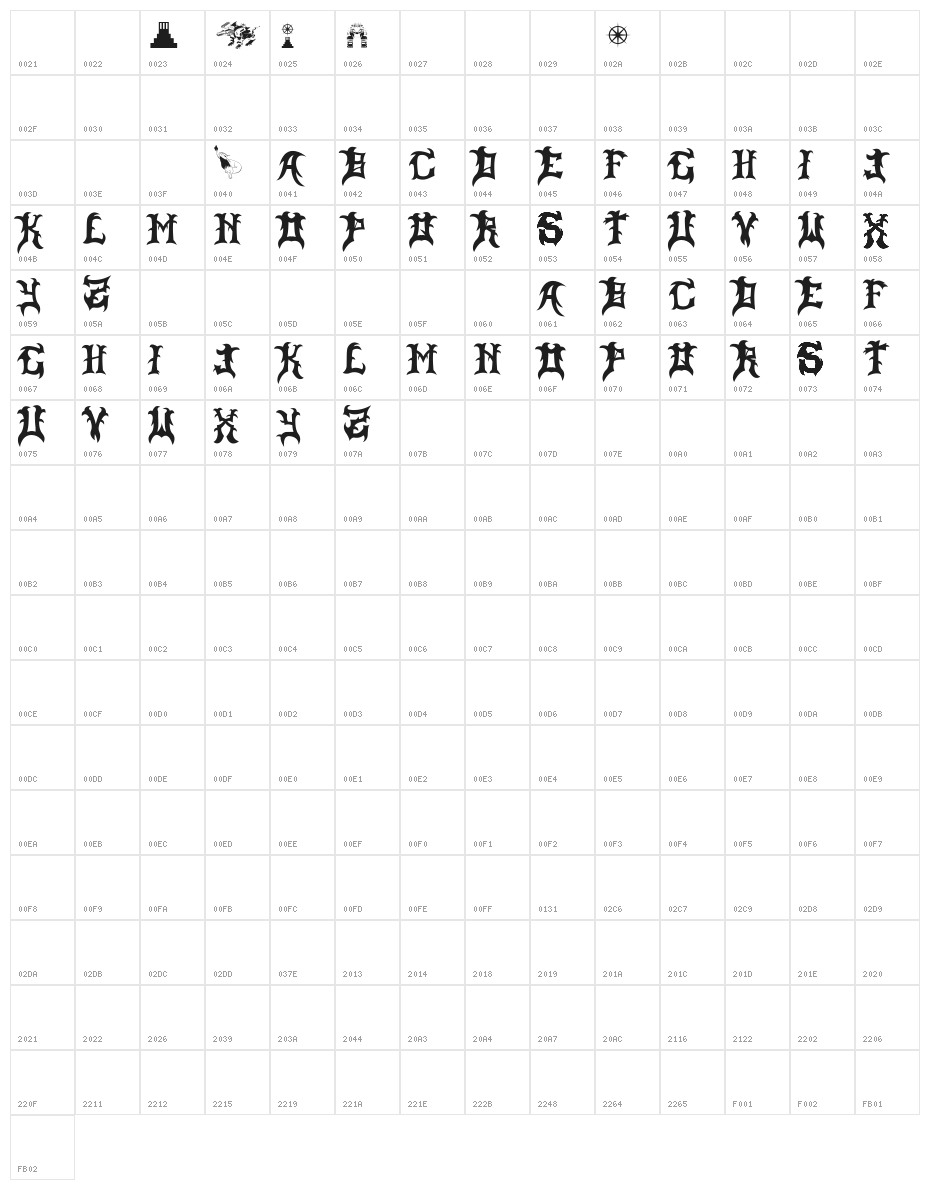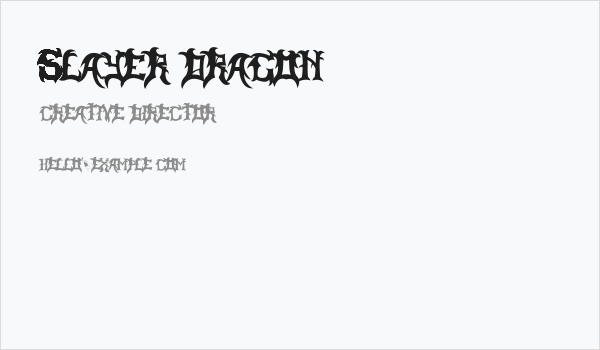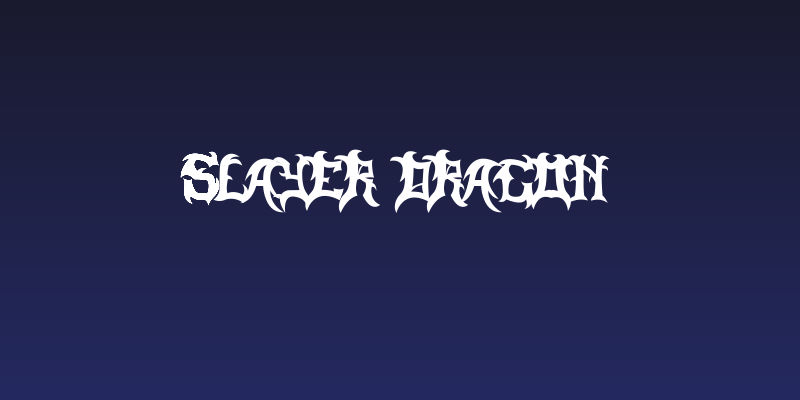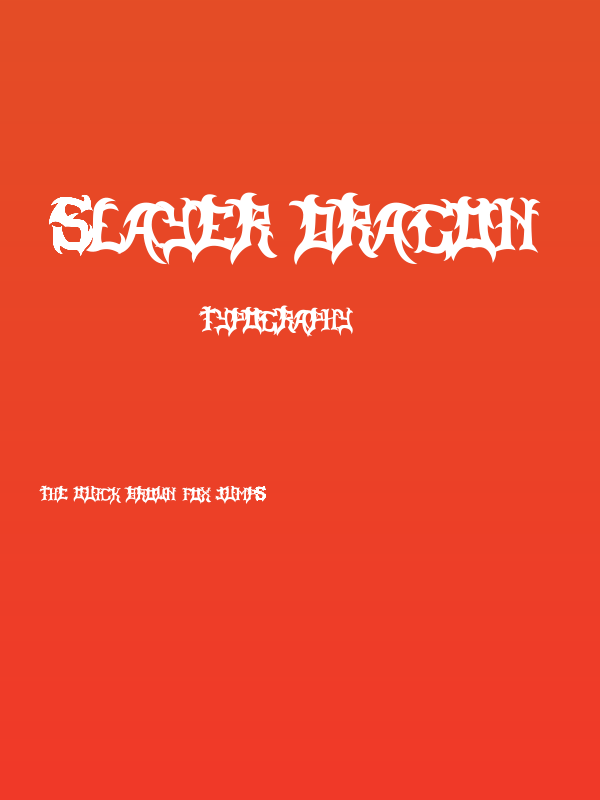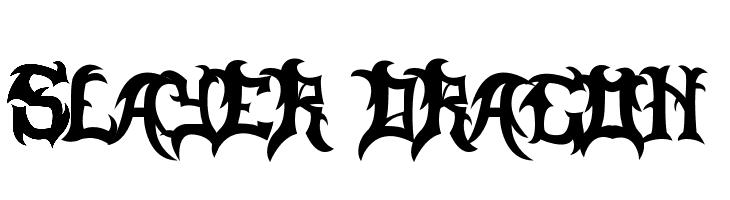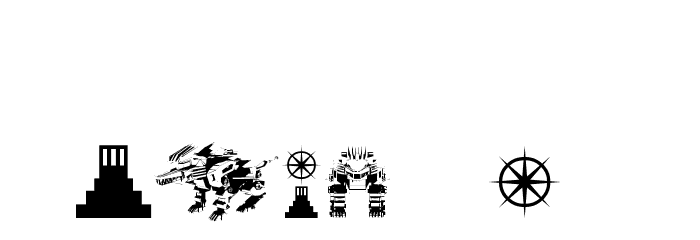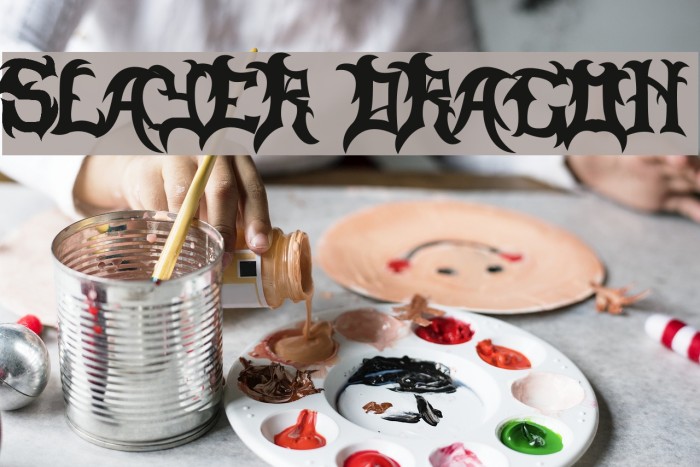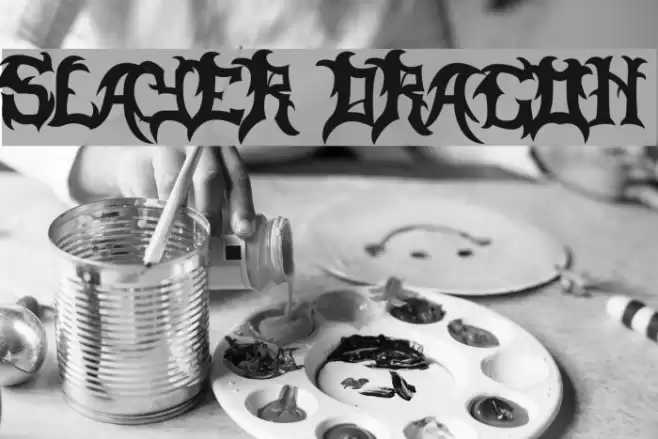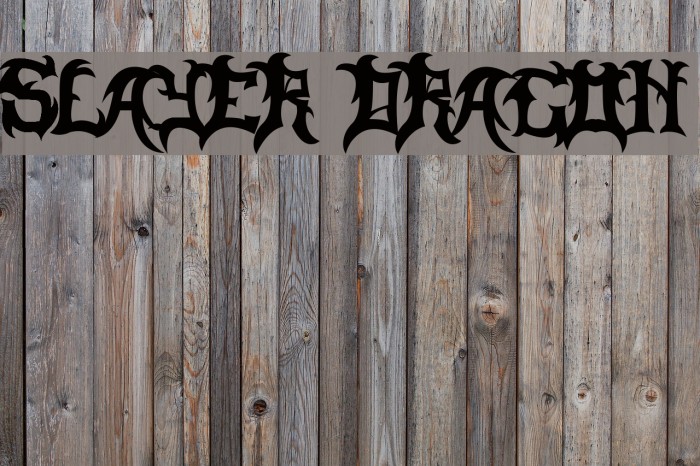
Slayer Dragon Font
| Kategorien | Gothic |
| Gesamtstil | Gothic, Decorative |
| Anwendungsfall | Logos, Headlines, Posters |
| Vorgeschlagene Projekte | Ideal for use in fantasy-themed designs, heavy metal band logos, video game titles, or any project requiring a dramatic and bold aesthetic. |